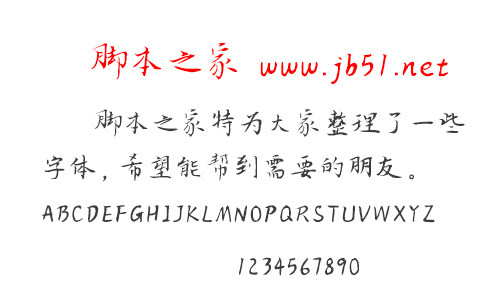
思雨相思無畔字體是思雨字庫推出的一款個性藝術(shù)字體,風(fēng)格比一般的字體更有特色,連貫字跡顯得干練而不凌亂,清新簡明,具有很好的視覺感,適合應(yīng)用于藝術(shù)設(shè)計、平面宣傳設(shè)計、網(wǎng)頁設(shè)計,書法字帖等領(lǐng)域,歡迎喜歡思雨相思無畔字體的朋友前來下載使用。